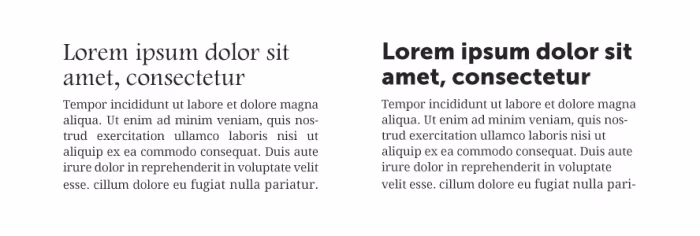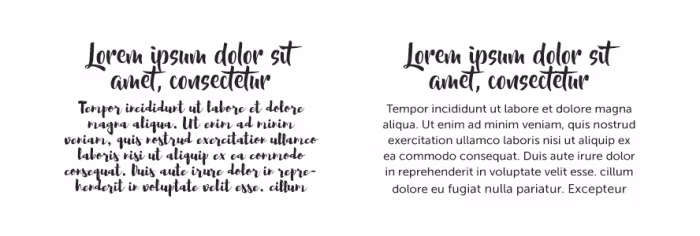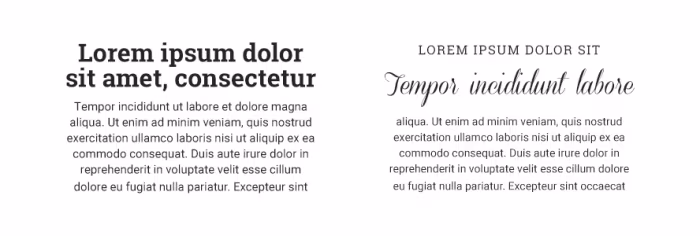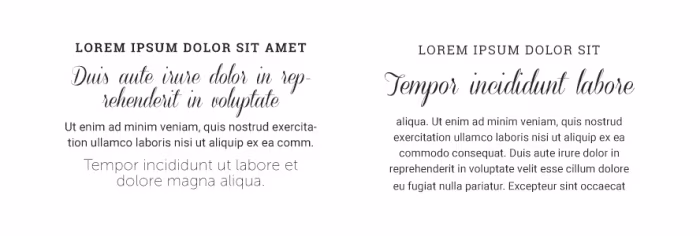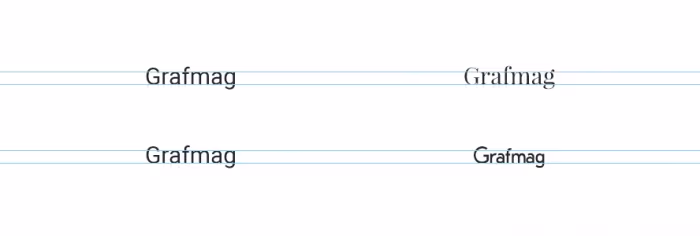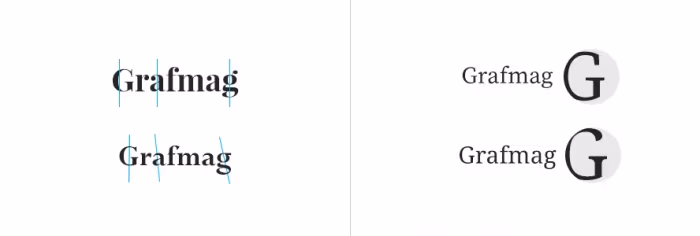
Dobór krojów, to jedna z kluczowych decyzji podczas rozpoczynania każdego procesu projektowego. Użyta typografia w znaczący sposób decyduje o odbiorze naszej strony, jej stylistyce i przede wszystkim – czytelności. Dobre i złe decyzje w tym zakresie mogą zmienić godziny pracy w sukces, albo sprawić, że będzie to czas stracony. W dzisiejszym artykule postanowiłam pochylić się nad podstawowymi zasadami łączenia krojów, pisać będę w szczególności o sieci, jednak zasady te są uniwersalne na tyle, że spokojnie możecie wykorzystać je także w innego typu projektach.
Kroje o różnej klasyfikacji
Pierwszą rzeczą o której należy pamiętać podczas dobierania do siebie krojów jest to, aby podchodziły one pod różne klasyfikacje. Innymi słowy, aby łączyć te szeryfowe z bezszeryfowymi, bezszeryfowe z ozdobnymi i temu podobnie, a unikać połączeń dwóch pism szeryfowych czy dwóch bezszeryfowych (chociaż to zrobić jest zdecydowanie łatwiej). Dzięki temu możliwe jest zachowanie odpowiedniego kontrastu, nie wprowadzamy także chaosu. Wybór takich połączeń jest bardzo bezpieczny, praktycznie każdy z klasycznych krojów szeryfowych będzie stosunkowo dobrze komponował się z każdym prostym krojem bezszeryfowym (w tym wypadku nie biorę pod uwagę tych geometrycznych, wąskich czy zawierających inne charakterystyczne cechy).
Na przykładzie po lewej zobaczyć możecie jak dwa kroje szeryfowe (Footlight MT Light, Droid Serif) kłócą się ze sobą w ramach jednego bloku tekstu. Pomimo tego, że jest im do siebie bliżej niż tym z prawej strony, połączenie to wygląda nienaturalnie i budzi opory. Z drugiej strony mamy przykład wykorzystania fontu Museo Sans w nagłówku i Droid Serif w treści. Jak widać, wyglądają one o wiele lepiej, nie mamy także problemu z rozróżnieniem dwóch sekcji treści.
Oczywiście od każdej zasady istnieją wyjątki. Podczas pracy z tekstem musimy w pierwszej kolejności myśleć o czytelności, a zasady mieć z tyłu głowy, bardziej aby się kontrolować, niż zabraniać sobie czegoś konkretnego tylko dla sportu. W przypadku łączenia krojów szeryfowych może zajść taka konieczność na przykład wtedy, kiedy wymarzony przez nas krój nagłówkowy słabo wygląda przy małej wielkości znaków, a z jakichś powodów chcemy zachować na stronie jedynie ten rodzaj pisma. W takim wypadku połączyć je oczywiście możemy, warto jednak pamiętać o kilku zasadach, które opiszę w ostatnim punkcie, powyższy przykład zdecydowanie nie jest jednym z tych dobrych.
Tylko jeden wyrazisty font
Wyraziste kroje, podobnie jak wyraziści ludzie, to takie istoty obok których ciężko przejść obojętnie i z drugiej strony – trudno wytrzymać z nimi w dużych ilościach, zbyt często lub kilkoma na raz. Jeśli wiec decydujemy się na wykorzystanie trudnych (szczególnie w sieci) krojów ozdobnych, musimy pamiętać, aby robić to z wyjątkową rozwagą i ostrożnością. Praktycznie nigdy nie powinno się składać dłuższych akapitów pismem bardzo ozdobnym, a zachować je tylko dla wyróżniania wyjątkowych części (na przykład krótkich cytatów, haseł), nieszczególnie nadają się one nawet do powtarzających się nagłówków.
Pomijając już kwestie wizualne (bo z nimi można się kłócić, szczególnie jeśli omawia się to z klientem), w tym wypadku istotniejsza jest  czytelność, a właściwie jej brak. Jak widać na przykładzie powyżej – wykorzystanie kolejnego kroju ozdobnego w treści akapitu sprawiło, że jest on praktycznie nieczytelny, każdy z elementów przykuwa sporo uwagi, nie wiadomo więc na czym się skupić (niewiele pomogłoby także zastosowanie tego samego fontu ozdobnego). W sytuacji przeciwnej wykorzystałam tekst ozdobny jako krótki nagłówek dla akapitu złożonego krojem bezszeryfowym. Takie połączenie z jednej strony przyciąga uwagę, z drugiej znacząco poprawia czytelność całości.
Maksymalnie trzy kroje
Kolejna zasada została mi przedstawiona w dość młodym wieku, przez niezawodny spinacz z programu Power Point. Każdorazowo, podczas próby wykorzystania większej niż 3 ilości fontów informował on, że nie jest to za dobra decyzja. Co prawda nie argumentował specjalnie swojej wypowiedzi, jednak zawsze zakładałam, że jeśli ktoś umie doradzić w tworzeniu wykresów, na pewno zna się też na typografii.
Zasada ta świetnie sprawdza się w projektowaniu, szczególnie stron internetowych. Podczas tworzenia kolejnych realizacji staram się wykorzystywać maksymalnie dwie różne rodziny, dobrane według powyższych punktów, jednak czasem to zbyt mało. Teksty nagłówkowe powinny wyróżniać się, nie mogą być jednak zbyt ozdobne, aby zachowały swoją czytelność. Treści akapitowe powinny być złożone w taki sposób, aby ich odbiór nie był niczym zaburzony. Czego potrzeba nam więcej? Czasem po prostu “tego czegoś”, co może dać nam nieco bardziej bajerancki font.
Powyżej zobaczyć możecie dwa przykłady. Z pierwszego z nich, całkiem poprawnego połączenia fontów Roboto Slab i Roboto, nieco wieje nudą. W drugim do tych samych dodałam krój Coneria Script i nieco pobawiłam się typografią. Treść ta nabrała zupełnie innego klimatu – zawsze musimy więc pamiętać co dokładnie chcemy osiągnąć i na jakim odbiorze nam zależy.
Co jednak, jeśli dodany jeszcze jeden?
Połączenie z poprzedniego przykładu wygląda spokojnie i jest w moim odczuciu eleganckie. W momencie, kiedy do całości dodamy kolejny krój, zaczynamy tworzyć chaos, wszystkiego jest po prostu za wiele i ciężko skupić się na jednej rzeczy, bo nie wiemy co jest najistotniejsze.
Zasada ta jest bardzo ogólna i jeśli sytuacja naprawdę tego wymaga i jest to Wasza świadoma decyzja, nie powinniście bać się śmiało łączyć fontów. Sieć jest pełna niezwykle inspirujących stron internetowych i projektów graficznych bazujących głównie na bardzo zróżnicowanej typografii. Projekty te jednak łączy jedna, bardzo istotna zasada – wykorzystywane fonty w większości znacząco się od siebie różnią, a my jako odbiorcy możemy być pewni, że efekt jaki oglądamy był zamierzony.